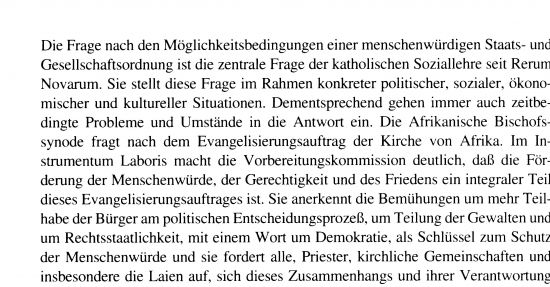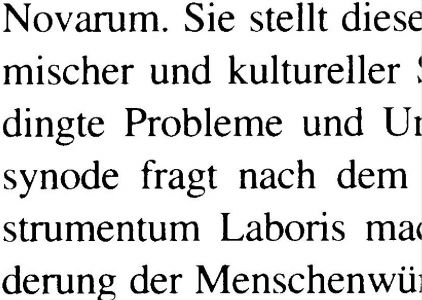
Schrift aus einem Buch von 1994
ich finde die unten abgebildete Schrift sehr angenehm zu lesen und mich würde interessieren, welche Schrift hier verwendet wurde.
Mit etwas weniger Text, dafür aber deutlich größer, könnten wir mehr anfangen – womit ich eventuelle Geniestreiche der Kollegen nicht ausschließen möchte.
Hier habe ich es nochmals etwas größer. Besser bekomme ich es nicht hin, da das Papier nicht mehr so gut ist (Kontrast beim scannen usw.). Dennoch schon mal Danke für den Versuch.